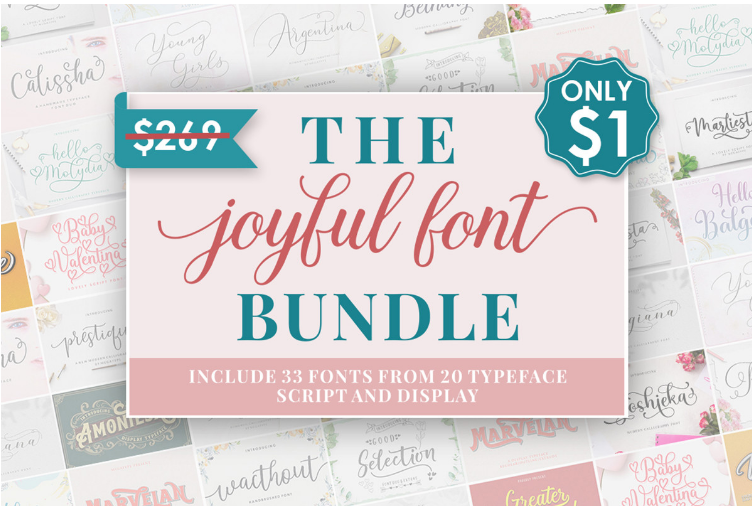
[Creativefabrica] The Joyful Font Bundle (Megatype)
Этот пакет шрифтов Joyful Font Bundle содержит 33 шрифта из 20 шрифтов, красиво оформленных и веселых! В этом наборе вы найдете уникальное сочетание современных и классических веселых стилей для создания идеальных надписей. Придайте своим дизайнам романтическую и веселую атмосферу, ведь каждый шрифт имеет свой собственный волшебный дизайн. Вы можете использовать его практически для всего, например, для заголовков блогов, плакатов, свадебных элементов, футболок, одежды, обложек книг, визиток, поздравительных открыток, брендинга, приглашений, журналов и цитат, и многого другого.